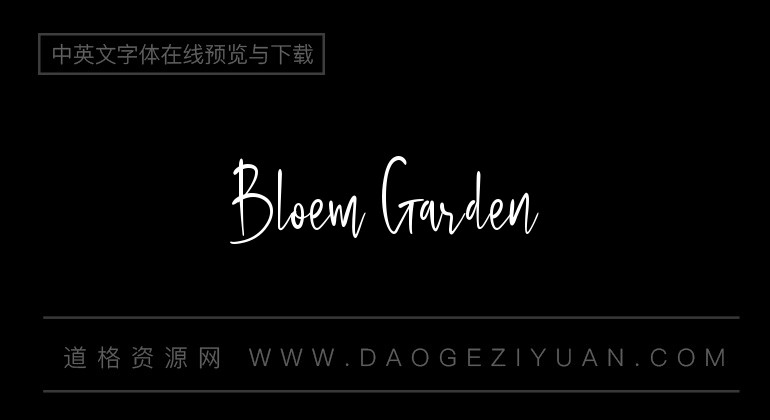
Bloem Garden 是一款由 Monotype 设计的草书字体,它的特点是清新、优雅、精致,具有浓浓的古典气息。它的字形弧度较大,笔画细腻,曲线优美,拥有比较大的视觉冲击力。它的笔画简洁,字形精致,让人眼前一亮,充满艺术感。它适用于招牌、商标、标识、婚礼邀请函等设计中,能够给设计带来更多的艺术气息。内容介绍
Bloem Garden是一款非常不错的手写艺术字体,具有很好的视觉感,适合于文化类的宣传设计、商业类品牌的广告和产品包装设计以及个性化文字排版等较多场景。